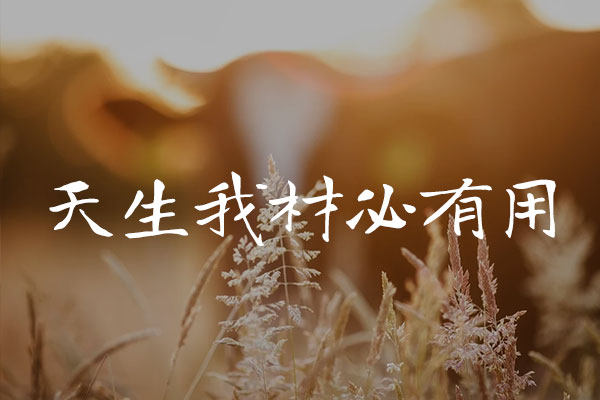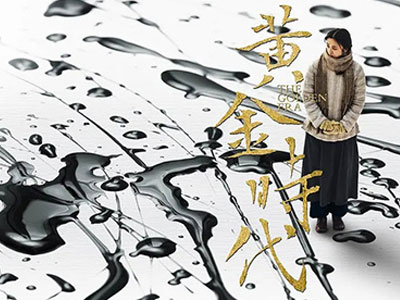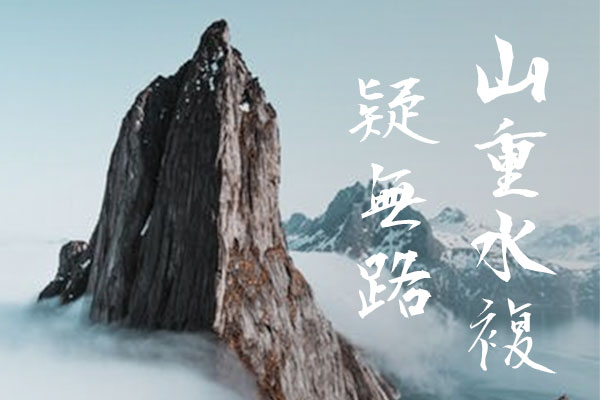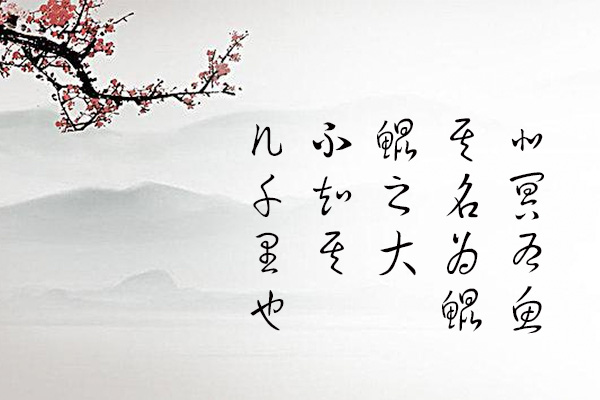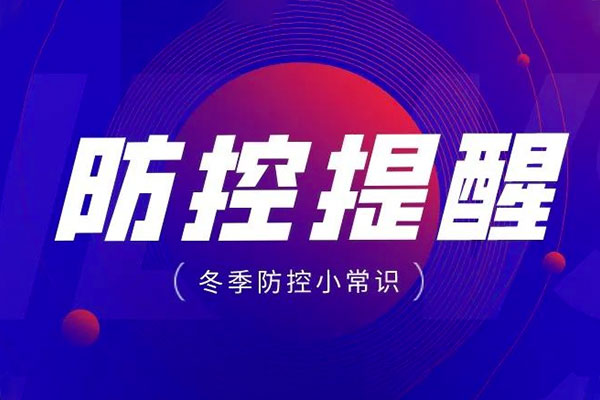
字体选择困难?用一篇文章帮你快速学会!
中国具有五千年文字历史,文字中所包涵的精髓,值得每一位设计师学习、继承与探究。设计师需要熟悉各种字体的风格特征,并能灵活运用字体进行编排设计,才能使作品的内容更清晰、更有条理地传达给读者。
字体是指文字的风格款式,也可以理解为文字的一种图形样式,不同的字体传达出不同的性格特征。文字不仅具有阅读的固有功能,同时肩负塑造版面视觉风格的审美功能。
在现代设计中常能够看到一些精心设计过的字体,以醒目而个性的形式出现,在进行信息传达的同时也被赋予了视觉个性,成为画面的焦点之一。
目前各大字库提供了各种版本、各种类型的字体供设计师使用。正因为字体类型繁多,使得版面设计成了一种很具有挑战的设计工作,设计师必须不断感受与体会,来安排好这些数量有限、潜力无穷的基本元素。
字体的特征
字体和人一样,有着不同的外部特征,也会散发出内在的气质,作为设计师,只有了解了每种字体的特性,才能对于字体的选择做出准确的判断。
字体种类繁多,为了让新手设计师能更快更好的选择字体,本期尝试化繁为简,分为「黑体」、「宋体」、「圆体」、「书法体」四大类,分析在它们在各种设计案例中的使用效果,推荐部分视觉效果较好,适用性较广的字体(优先推荐免费商用字体)。仅代表个人观点,供大家参考。
广义上说,没有衬线的字体都通常称为黑体,黑体是对字面呈正方形、笔画横平竖直且等粗类字体的统称,又被叫做方体或等线体。
简洁和规矩的黑体在气质上没有太大的个性,它适用的范围比较大,可塑性很强,通过字体的放大或者变形,就可以表现出不同的气质。各大字库也开发有各有特点的黑体,这里推荐的是三款免费商用字体:「思源黑体」、「阿里巴巴普惠体」、「OPPOSans」。
黑体醒目、结构清晰,简洁有力的字形风格能使版面显得庄重醒目并富有现代感。无论是识别性、适用面、视觉效果都是标题字体中的首选,新手使用也不容易犯错,唯一的缺点是个性不足,用得不好会显得平庸。 适用在各种正式、严谨的场合和让人产生信赖感的政府、企业、医疗行业等。
由于汉字笔划多,小字黑体清晰度较差,所以一开始主要用于文章标题。但随著制字技术的精进,已成为最多变、用途最广泛的基本字体,无论标题还是内文、注释都可以胜任。较粗的黑体适用于标题的表现,而较细黑体适用于排印正文。
黑体高度的统一性可以让字体本身对眼睛刺激降到最低,而把更多的注意力放在文字表达的内容上,是正文排版的首选字体。正文强调的是字体「读」的功能性,为正文选择黑体的目的是让读者轻松舒适地进行阅读,让读者专注于文字所表达的内容,通过合理的排版可以提升阅读体验。
黑体可塑性很强,由黑体衍生出大量的字体,基于黑体的基本特征,加入了独特的设计个性,并有着较大「字面率」,视觉冲击力很强,能快速吸引受众的眼球,非常适合标题用字,促销用字,广告语用字等视觉环境。
推荐6款免费商用、8款非免费商用的黑体衍生字体:
笔画较粗的黑体具有男性特点,醒目、粗犷、硬朗、具有力量感,视觉冲击力很强,能快速吸引受众的眼球,非常适合促销用字的广告语。常用在体育、汽车、游戏、电器、建筑等行业:
△ 应用场景
笔画较细的黑体,简约、高雅、细致,有女性特点,适合服装、化妆品、食品等行业。这里推荐使用思源黑体较细的字形和三款免费商用字体:
△ 应用场景
宋体字笔画横平竖直,横细竖粗,棱角分明,结构严谨,整齐均匀,有极强的笔画规律性,从而使人在阅读时有一种舒适醒目的感觉。
各大字库也开发有各有特点的宋体,这里推荐的是免费商用字体「思源宋体」,和使用较多、视觉效果较好的的7款宋体:
笔画教粗的宋体适合用做标题或副标题,笔画教细的宋体拥有很高的阅读性,主要用于正文排版。宋体优雅古典、端庄秀丽,用于时尚类、文化类设计时,会体现出精致的美感和独特的人文气质。适用运用在具有女性特征的时尚、服装、化妆品等行业和具有文化、历史感的设计风格中。
宋体和黑体是现代设计中运用最多的字体,既有良好的观赏性还具备较好的阅读性,用好宋体和黑体也是现代设计师必须具备的基本功。
圆体由黑体演变而来,在笔画的拐角处和其末端为圆弧状。由圆体又衍生出大量卡通字体,增加了趣味性和活泼感。
接下来推荐的字体非常适合运用在可爱活泼设计中,针对需要体现亲和力的儿童、女性、宠物类产品、轻松休闲的食品、家居用品等,会有不俗的表现力,常常能达到「画龙点睛」的效果。
△ 应用场景
书法字体具有丰富的表现力和艺术感染力,或潇洒流畅、泼墨自如;或清新儒雅、端庄秀丽。形式多姿多彩,富有节奏感和韵律美,具有极强的视觉冲击力,能够为画面增添无穷的魅力。书法艺术的恰当运用,会给人以极高的审美境界,它的感染力是美术字所不能替代的。
随着电脑字库的不断发展,很多传统书体形式都被开发成了字体,首先推荐的是3款免费商用书法字体:
书法字体自身带有律动韵味与艺术感气质,具有较强视觉张力,很是醒目。常用于体现传统文化的中国风设计中,以及艺术感强的历史文化画面中。适用于需要营造古典文化的茶、酒等产品,和需要体现雅风韵味、大气磅礴的地产、电影海报等设计中,有着强烈的人文气息,具有丰富的表现力和艺术感染力。
△ 应用场景
硬笔书法字体是模仿手写笔触的字体,字形多变,多为优雅洒脱的行书,常使用在体现传统文化,模拟书写亲切感设计中。推荐3款免费商用和5款非免费商用硬笔书法字体
字体的选择
了解字体的风格特点后,我们可以根据目标受众、项目调性、行业属性等方式确定字体类型,再从字体类型中选择特定字体。
1. 目标受众
在选择字体的时候,设计师需要考虑到设计项目受众的喜好,根据不同的目标受众需求选择合适的字体。
如笔画纤细、柔和的字体,从气质上就显得比较女性、温柔;而笔画粗壮、刚硬的字体,则更有男性的阳刚气质。
笔画活泼、圆润的字体,从气质上显得比较儿童、低幼;而古朴、历史感的字体,则更有岁月痕迹、文化沉淀的气质。
2. 项目调性
字体可以传递版面设计的气质,在确定标题字体前,要知道项目调性是什么,根据具体风格来选择相应类型的字体。表现男性、商业、现代、科技,可以优先选择黑体;表现优雅、端庄、文化、艺术,可以优先选择宋体;表现可爱、活泼、轻松、休闲,可以优先选择圆体;表现中国文化、古典、传统,可以优先选择书法体等。
3. 行业属性
每个行业、商品,都有着固定的气质,不同的字体有着不同的特点,选择的字体需要和行业属性相吻合。体育、汽车、游戏、电器、建筑等行业,较适合使用黑体;时尚、服装、化妆品等行业,较适合使用宋体;儿童、女性、宠物、食品等行业,较适合使用圆体;茶、白酒等要体现传统文化的行业,较适合使用书法字体。
结 语
本期通过「黑体」、「宋体」、「圆体」、「书法体」四大类字体,分别分析在它们在各种设计案例中的使用效果。我们可以根据目标受众、项目调性、行业属性等方式确定字体类型,再从字体类型中选择特定字体。字体种类很多,是一个阵容庞大的体系,希望通过本期的字体推荐在你选择字体时得到一些借鉴和启发,并有效提高工作效率。